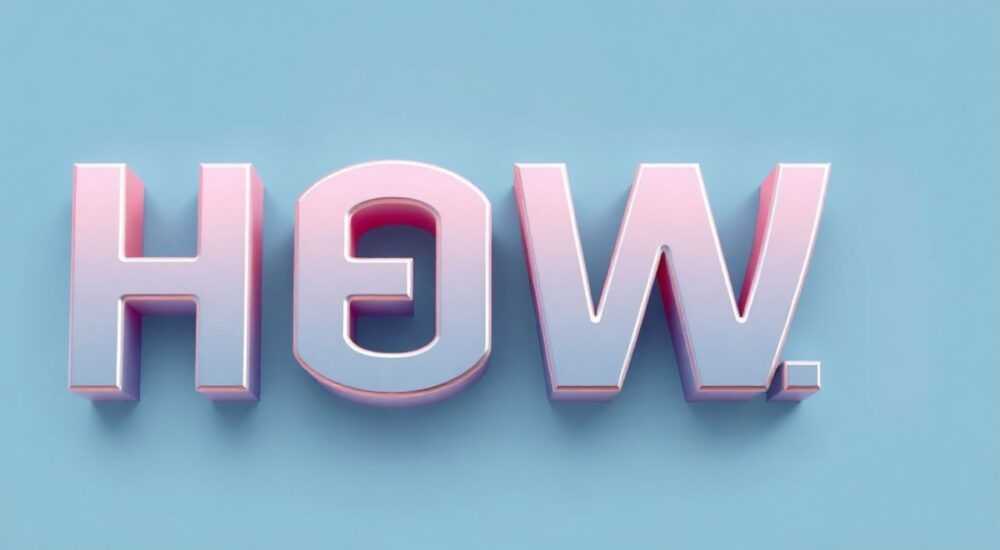
Как сделать объемный шрифт в фотошопе
Объемный шрифт в Adobe Photoshop — это мощный инструмент для создания эффектных заголовков, логотипов и графических элементов. Он добавляет глубину и выразительность тексту, превращая плоские буквы в трехмерные объекты, которые можно детально настраивать: регулировать освещение, тени, материал поверхности и перспективу. Такой эффект особенно востребован в брендинге, рекламе и цифровом дизайне.
Основные методы создания объемного шрифта
В Photoshop существует несколько подходов к созданию объемного текста. Каждый из них подходит для разных задач: от простых баннеров до сложных 3D-композиций. Выбор метода зависит от требований проекта, уровня подготовки дизайнера и версии программы.
Первый и самый современный путь — использование встроенной 3D-системы. Начиная с версий Photoshop CS6 и CC, Adobe внедрил полноценный 3D-движок, позволяющий преобразовывать текст в трехмерный объект с возможностью вращения, масштабирования и настройки материалов. Этот метод дает максимальную свободу, но требует больше ресурсов компьютера.
Второй способ — имитация объема с помощью стилей слоя. Это классический, но по-прежнему эффективный подход. Через параметры «Обводка», «Тень», «Внутренняя тень», «Наложение градиента» и «Тиснение» можно добиться реалистичного эффекта глубины без активации 3D-режима. Преимущество этого метода — легкость, совместимость и возможность быстрого редактирования текста.
Третий, более трудоемкий, но гибкий вариант — ручное построение объема с помощью дублирования и сдвига текстовых слоев. Этот метод часто используется в типографских проектах, где важна точность и контроль над каждым миллиметром формы.
- 3D-текст — для профессиональных макетов, презентаций, анимаций.
- Стили слоя — для веб-дизайна, соцсетей, печатной продукции.
- Ручной метод — для кастомной типографики, логотипов, арт-проектов.
Выбор стратегии напрямую влияет на производительность, качество результата и сроки выполнения работы.
Создание 3D-текста через функцию 3D
Самый зрелищный способ придать тексту объем — использовать 3D-преобразование. Процесс состоит из нескольких этапов, каждый из которых можно настроить под конкретную задачу.
Шаг 1: Создание текстового слоя
Начните с обычного текстового слоя. Выберите инструмент Текст (T), укажите нужный шрифт, размер и цвет. Лучше использовать жирные, четкие шрифты — они лучше передают объем. Избегайте слишком тонких или декоративных гарнитур, если планируете сильное выдавливание.
Шаг 2: Преобразование в 3D-объект
Выделите текстовый слой в палитре слоев. Перейдите в меню 3D → Новый 3D-объект из выбранного слоя → Выдавить. Photoshop автоматически создаст 3D-объект с глубиной по умолчанию.
Откроется панель 3D, где вы можете управлять камерой, светом и свойствами объекта. На холсте появится объемный текст, который можно вращать с помощью инструмента Вращение 3D-объекта.
Шаг 3: Настройка глубины выдавливания
В панели 3D выберите вкладку Выдавливание. Здесь вы найдете ползунок Глубина, регулирующий толщину текста. Значение по умолчанию — 0,5 см, но его можно увеличить до 5–10 см для более выраженного эффекта.
Также можно настроить:
- Сглаживание — делает края скругленными;
- Кап-материал — внешний вид передней и задней граней;
- Боковые стенки — текстура и цвет боковых поверхностей.
Шаг 4: Работа с камерой и ракурсом
Инструменты камеры позволяют изменить перспективу. Используйте:
- Вращение 3D-камеры — для изменения угла обзора;
- Панорамирование — сдвиг изображения по осям;
- Масштабирование — приближение/удаление.
Для сохранения композиции рекомендуется выбрать предустановленный вид, например «Передний» или «Изометрический».
Параметр |
Описание |
Рекомендуемое значение |
Глубина выдавливания |
Толщина объема буквы |
1–3 см |
Сглаживание |
Скругление краев |
5–15 px |
Материал |
Текстура поверхности |
Металл, пластик, матовый |
Ручной способ объема через стили слоя
Если 3D-функции недоступны или вы хотите быстро получить результат, воспользуйтесь стилями слоя. Этот метод работает во всех версиях Photoshop и идеален для плоского, но визуально объемного текста.
Шаг 1: Добавление внутренней тени
Дважды щелкните по текстовому слою, чтобы открыть Стили слоя. Активируйте Внутренняя тень. Установите угол 120°, расстояние 2–5 px, размер 3–7 px. Это создаст эффект углубления верхнего края буквы.
Шаг 2: Применение градиента
Добавьте Наложение градиента. Выберите линейный градиент от светлого к темному цвету. Направление — сверху вниз. Это имитирует падение света и усиливает объем.
Шаг 3: Обводка и тень
- Обводка — добавьте тонкую (1–2 px) темную рамку по внешнему краю. Это подчеркнет форму.
- Тень — установите небольшую тень (расстояние 3–5 px, размытие 2–4 px), чтобы текст не «прилипал» к фону.
Шаг 4: Тиснение (по желанию)
Для дополнительного эффекта используйте Тиснение с режимом наложения «Осветление основы». Глубина — 1–2 px. Это придаст тексту рельефность, особенно на темных фонах.
Работа с материалами и освещением в 3D
Качественный объемный текст выглядит реалистично только при правильном освещении и материалах. В 3D-режиме Photoshop позволяет полностью контролировать эти параметры.
Настройка источников света
В панели 3D выберите вкладку Свет. По умолчанию активен один источник — Infinite Light. Вы можете:
- Изменить направление света, перетаскивая маркер на сцене;
- Добавить второй источник (например, Spotlight) для акцентного освещения;
- Отрегулировать интенсивность и цвет света.
Рекомендуется использовать два источника: основной (мягкий, рассеянный) и вспомогательный (точечный, для бликов).
Применение материалов
Каждая часть 3D-текста — передняя грань, боковые стенки, задняя грань — может иметь свой материал. Щелкните по нужной области в панели 3D и выберите материал из библиотеки:
- Plastic — для ярких, глянцевых поверхностей;
- Metal — для металлического блеска;
- Matte — для матовых, немецких текстур.
Можно загрузить собственные текстуры (JPG/PNG) и наложить их как диффузные карты.
Экспорт и использование объемного текста
После завершения работы важно правильно экспортировать результат. Формат зависит от цели использования.
Цель |
Рекомендации |
Печать |
PNG, TIFF, PSD |
Разрешение 300 dpi, CMYK (если требуется) |
Веб / Соцсети |
PNG, JPEG |
Сжатие без потерь, RGB |
Анимация |
PSD + After Effects |
Сохранить слои отдельно |
Если вы использовали 3D, можно экспортировать сцену как OBJ или DAE для дальнейшей работы в Cinema 4D или Blender. Однако учтите: после экспорта теряются некоторые стили и эффекты Photoshop.
- Слишком большая глубина — делает текст нечитаемым. Оптимальная толщина — 10–30% от высоты буквы.
- Неестественное освещение — тень и блик должны быть согласованы. Все источники света должны быть направлены примерно в одну сторону.
- Растеризация текста до настройки — лишает возможности редактировать содержание. Всегда работайте с векторным текстом до финального экспорта.
- Использование прозрачного фона без тени — объем теряется. Добавляйте легкую тень или фоновую подложку.
Он также отмечает, что для брендовых проектов важно тестировать объемный текст в разных условиях: на мобильных экранах, при печати, на темных и светлых фонах. То, что выглядит эффектно на мониторе, может потеряться в реальности.
Создание объемного шрифта в Photoshop — это не просто технический навык, а важный элемент визуальной коммуникации. Будь то 3D-рендер или имитация глубины через стили, правильный подход делает текст доминантой композиции. Главное — понимать цель: для чего нужен объем, где он будет использоваться и какой эмоциональный отклик должен вызвать.
- Начинайте с векторного текста для гибкости редактирования.
- Настройте свет и тень в соответствии с общей композицией.
- Используйте 3D-функции для сложных проектов, а стили слоя — для оперативных задач.
- Экспортируйте в правильном формате в зависимости от цели.
- Тестируйте результат на разных устройствах и фонах.